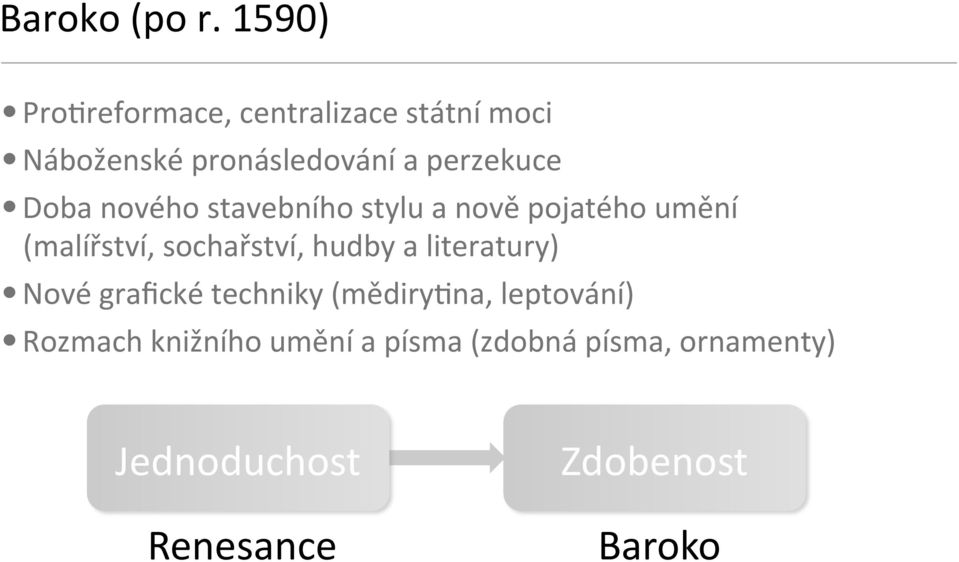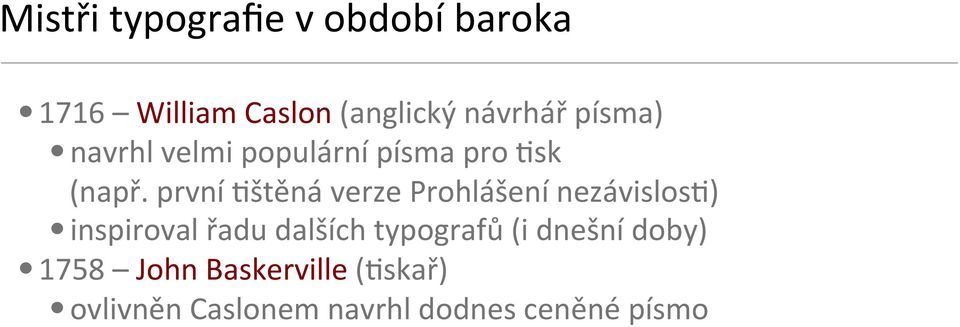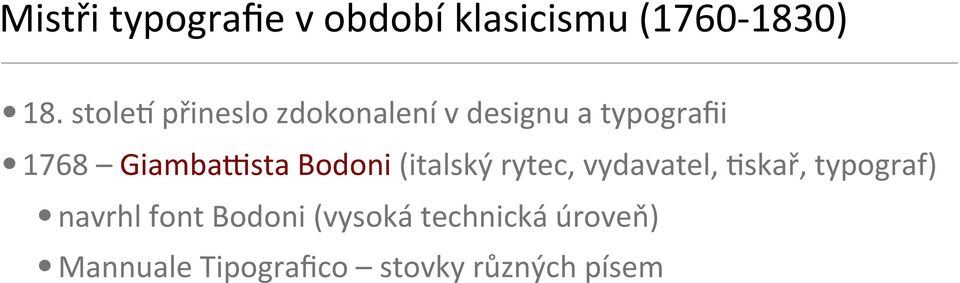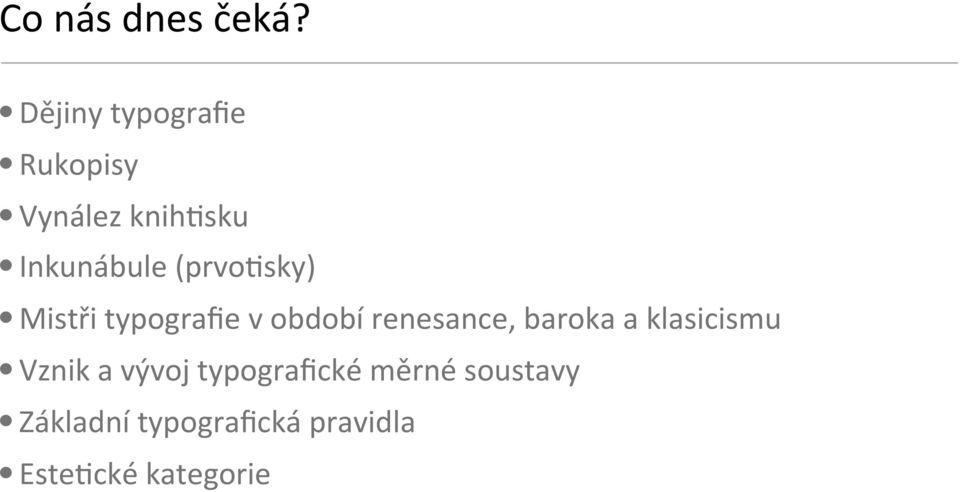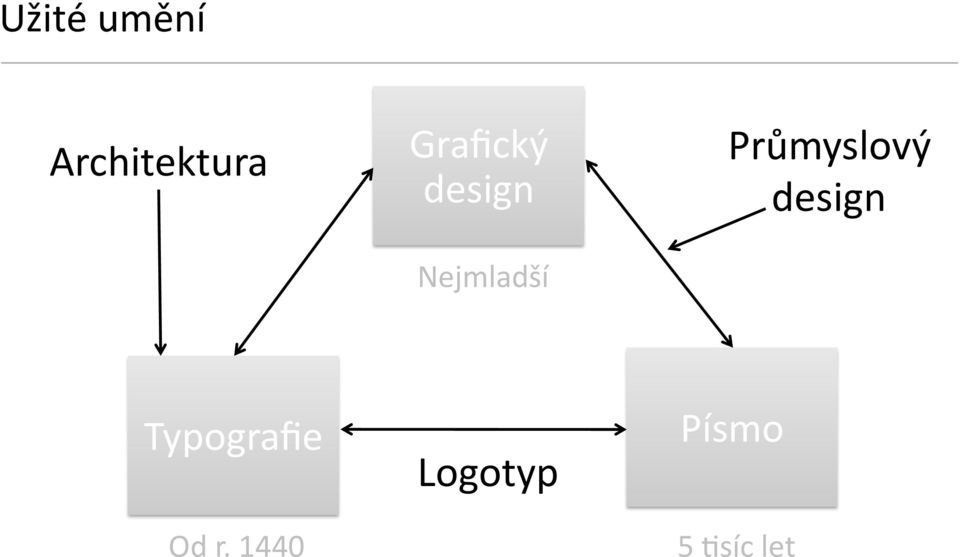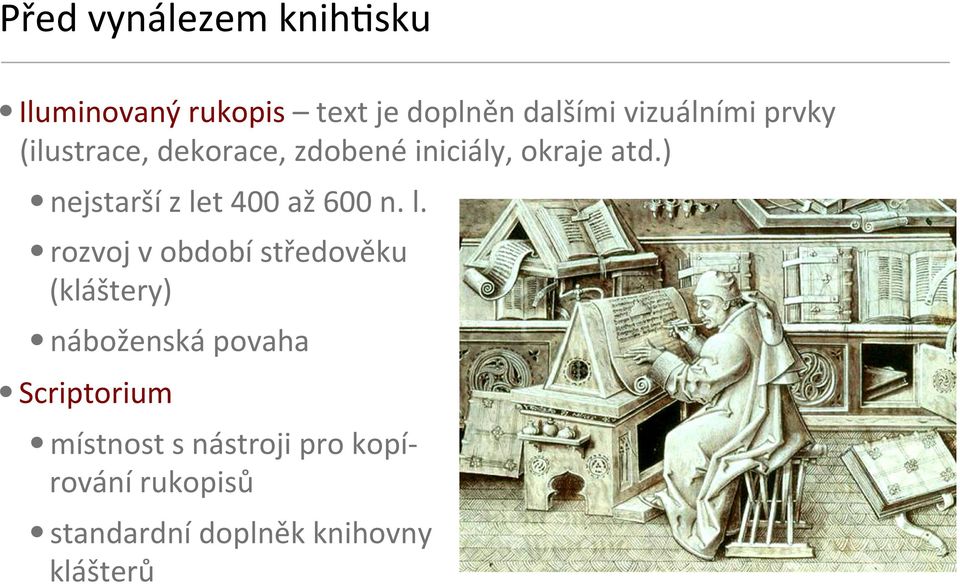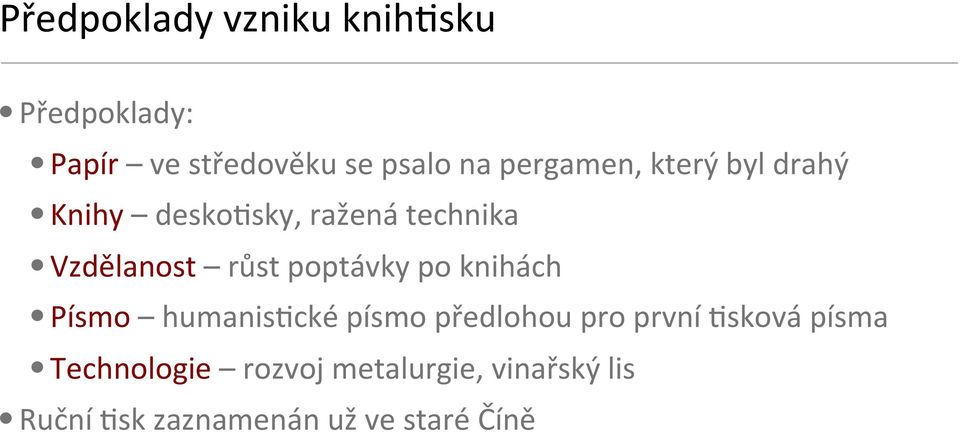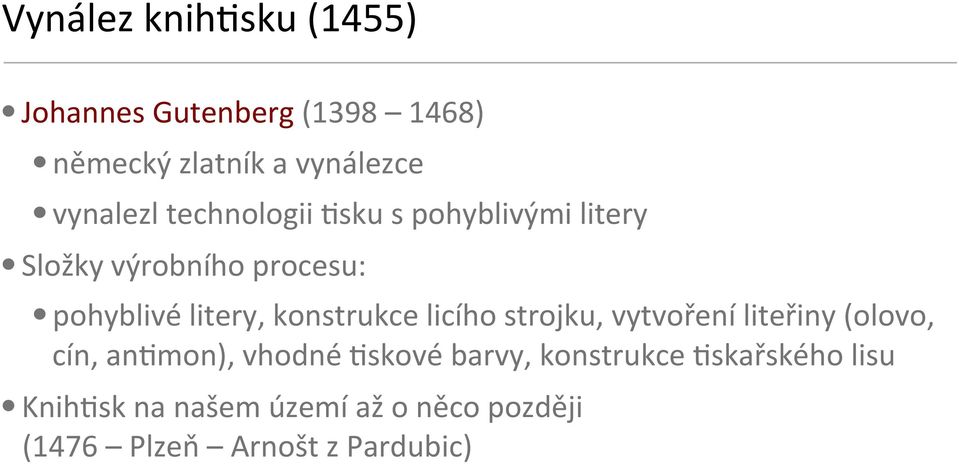
Typografie. Jana Dannhoferová Ústav informa3ky PEF MZLU v Brně Audiovizuální komunikace (AVK)
1 Typografie Jana Dannhoferová Ústav informa3ky PEF MZLU v Brně Audiovizuální komunikace (AVK)
2 Co nás dnes čeká? Dějiny typografie Rukopisy Vynález knih3sku Inkunábule (prvo3sky) Mistři typografie v období renesance, baroka a klasicismu Vznik a vývoj typografické měrné soustavy Základní typografická pravidla Este3cké kategorie
3 Užité umění Architektura Grafický design Nejmladší Průmyslový design Typografie Od r Logotyp Písmo 5 3síc let
4 Zdokonalování forem komunikace Ústní forma Rukopis Tisk Elektronická forma
5 Dějiny typografie Typus znak vzor, Gráfo píši (doslovně psaní znaků) Typografie se řadí mezi užité umění Význam: organizace písma v ploše po vynálezu knih3sku obor zahrnující sazbu a knih3sk dnes este3cká úprava sazby Historie typografie spojena s vývojem 3štěné knihy
6 Před vynálezem knih3sku Iluminovaný rukopis text je doplněn dalšími vizuálními prvky (ilustrace, dekorace, zdobené iniciály, okraje atd.) nejstarší z let 400 až 600 n. l. rozvoj v období středověku (kláštery) náboženská povaha Scriptorium místnost s nástroji pro kopí- rování rukopisů standardní doplněk knihovny klášterů
7 Renesance (14. až 16. stolel) Renesance (znovuzrození) Humanismus hospodářský růst, rozvoj vědy a umění Návrat ke klasickým (an3ckým) konceptům stylu, umění a krásy (používání perspek3vy v malířství) Znovuobjevené principy se využívaly také v designu knih a v umístění textových čásl na stránce Přechod od středověku k novověku objevení Ameriky (1492) objevení knih3sku (1455)
8 Předpoklady vzniku knih3sku Předpoklady: Papír ve středověku se psalo na pergamen, který byl drahý Knihy desko3sky, ražená technika Vzdělanost růst poptávky po knihách Písmo humanis3cké písmo předlohou pro první 3sková písma Technologie rozvoj metalurgie, vinařský lis Ruční 3sk zaznamenán už ve staré Číně
9 Vynález knih3sku (1455) Johannes Gutenberg ( ) německý zlatník a vynálezce vynalezl technologii 3sku s pohyblivými litery Složky výrobního procesu: pohyblivé litery, konstrukce licího strojku, vytvoření liteřiny (olovo, cín, an3mon), vhodné 3skové barvy, konstrukce 3skařského lisu Knih3sk na našem území až o něco později (1476 Plzeň Arnošt z Pardubic)
10 Prvo3sky (inkunábule) Z la3nského cunabulis v kolébce, v plenkách Prvo3sky končí zhruba rokem 1500 Dva typy inkunábulí: dřevorytecké vyřezané z jednoho bloku dřeva pro každou stránku typografické s výměnným písmem pro 3skové stroje Knih3sk využíval národní písma dané země: Itálie rotunda, an3kva Francie, Anglie an3kva, rotunda, textura, bastarda Německo švabach, fraktura Střední Evropa textura, bastarda
11 Prvo3sky (inkunábule) Tiskárny většinou pouze ve velkých městech (učenci, právníci, šlech3ci atd.) Design knih přechodné období iniciály a zdobení ještě odkazuje na středověk knihy však už nejsou tak tmavé a hustě psané odlehčení (někdy je to přikládáno snížením nákladů na výrobu zejména levnějšímu dovozu papíru) Papír od slova papyrus (Egypt již v roce 3000 př. n. l.) v období prvo3sků se papír vyráběl z hader později z celulózy (19. stolel)
12 Mistři vizuálního stylu v období renesance 1490 Leonardo da Vinci (malíř, sochař, architekt, inženýr, vědec) výkresy, ilustrace mimořádné rozložení stránky 1501 Aldus Manu3us (humanis3cký učenec, později 3skař) poprvé použil kurzívu v knihách 1529 Geofry Tory (jeden z největších 3skařů v Paříži své doby) napsal pojednání o konstrukci velkých římských písmen (kniha: Champs Fleury) odvodil proporce verzálek ze vzájemných poměrů lidského těla tvůrce francouzské typografické školy 1541 Claude Garamond (pařížský vydavatel a přední návrhář písma své doby) navrhl písmo Garamond Granjon font, který nejvíce připomíná původní Garamond
13 Základy grafického designu Albrecht Duerer ( ) německý malíř, řezbář, rytec a matema3k důležitá osobnost grafického a knižního designu Kniha Unterweysung der Messung (Kurz umění měření) Symetrie - slavná kniha o základech designu (geometrie plochy, principy perspek3vy objevené v Itálii, jejich použil pro architekturu, malířství a písmo)
14 Baroko (po r. 1590) Pro3reformace, centralizace státní moci Náboženské pronásledování a perzekuce Doba nového stavebního stylu a nově pojatého umění (malířství, sochařství, hudby a literatury) Nové grafické techniky (mědiry3na, leptování) Rozmach knižního umění a písma (zdobná písma, ornamenty) Jednoduchost Renesance Zdobenost Baroko
15 Mistři typografie v období baroka 1692 Philippe Grandjean (francouzský rytec) navrhl písmo Roman (Romain du Roi) pro krále Ludvíka XIV.
16 Mistři typografie v období baroka 1716 William Caslon (anglický návrhář písma) navrhl velmi populární písma pro 3sk (např. první 3štěná verze Prohlášení nezávislos3) inspiroval řadu dalších typografů (i dnešní doby) 1758 John Baskerville (3skař) ovlivněn Caslonem navrhl dodnes ceněné písmo
17 Mistři typografie v období baroka 1737 Pierre Simon Fourier (francouzský typografický teore3k) navrhl písmo Fourier publikoval teore3ckou práci o minimálních rozestupech mezi písmeny se zachováním čitelnos3 (typografický manuál)